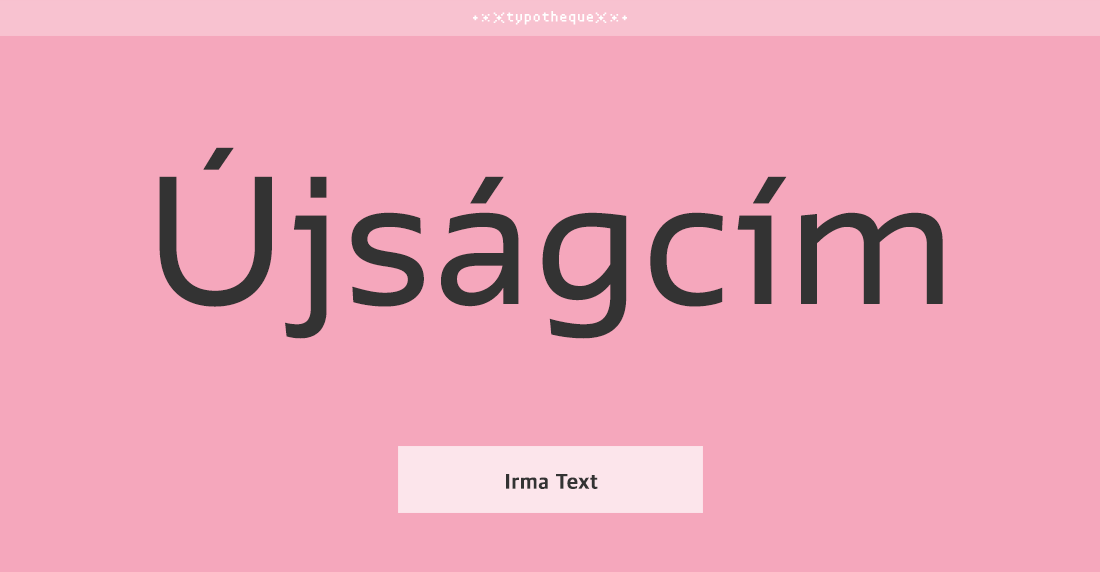
- IrmaText Std는 두 개의 모순되는 건축 원리의 균형을 맞춘 유연한 형태의 산 세리프체이다.
이미 출시된 Irma Display의 기하학적 구조를 계승하면서 손으로 쓴 듯한 형태를 결합하여 세련되면서도 차분하다.
폰트 정보 폰트명 Irma Text Std 구분 고딕 디자인디렉팅 Peter Biľak 출시년도 2012